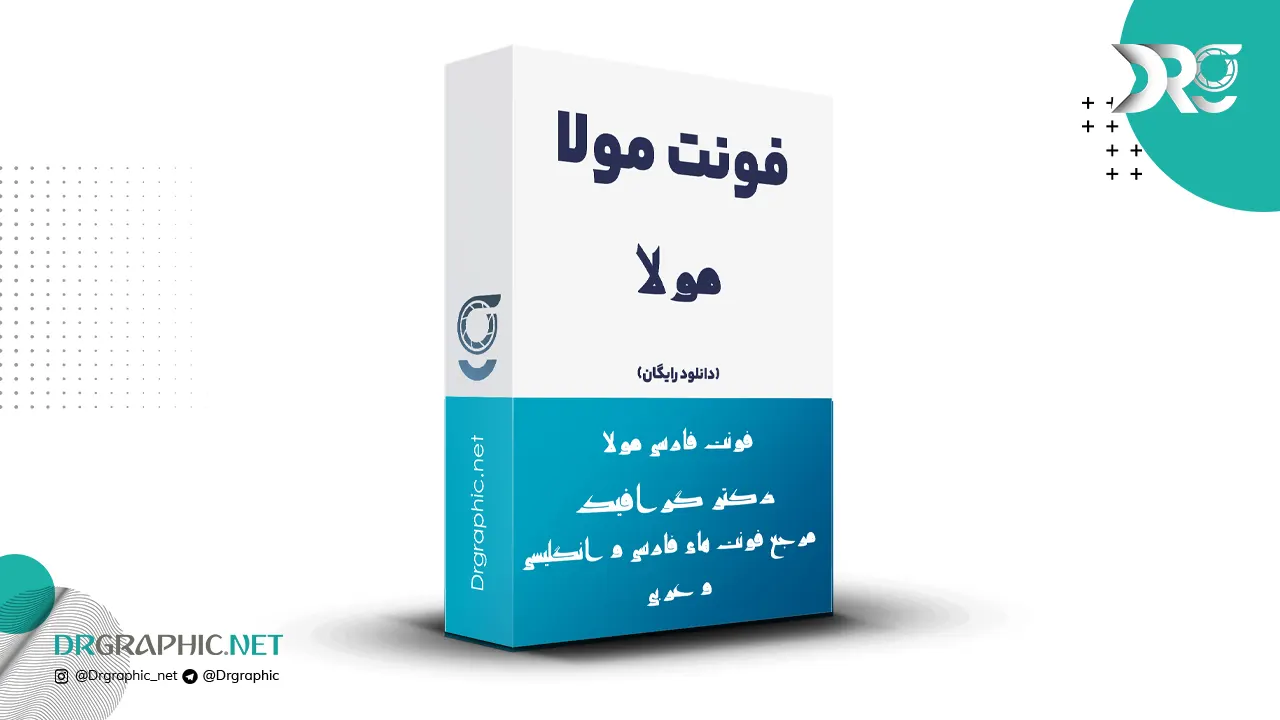
دانلود فونت کوفی مولا Mola
فونت مولا از خط کوفی که از روی قرآن منسوب به حضرت علی (ع) ساخته شده و دارای نقطه و حروف ترکیبی و اعراب کامل می‌باشد توسط آقای حسین زاهدی طراحی شده است.